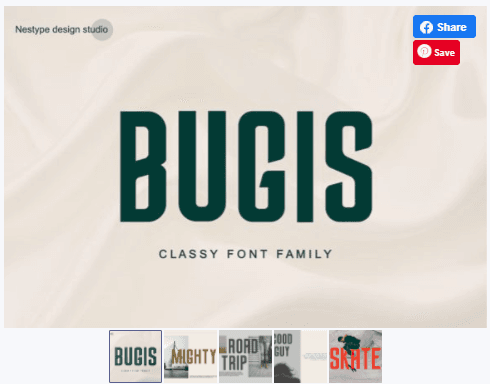
Bugis Font
Bugis - приятный и удобный дисплейный шрифт. Его естественный и уникальный стиль делает его невероятно подходящим для большого количества дизайнов. Единственным ограничением является ваше воображение!